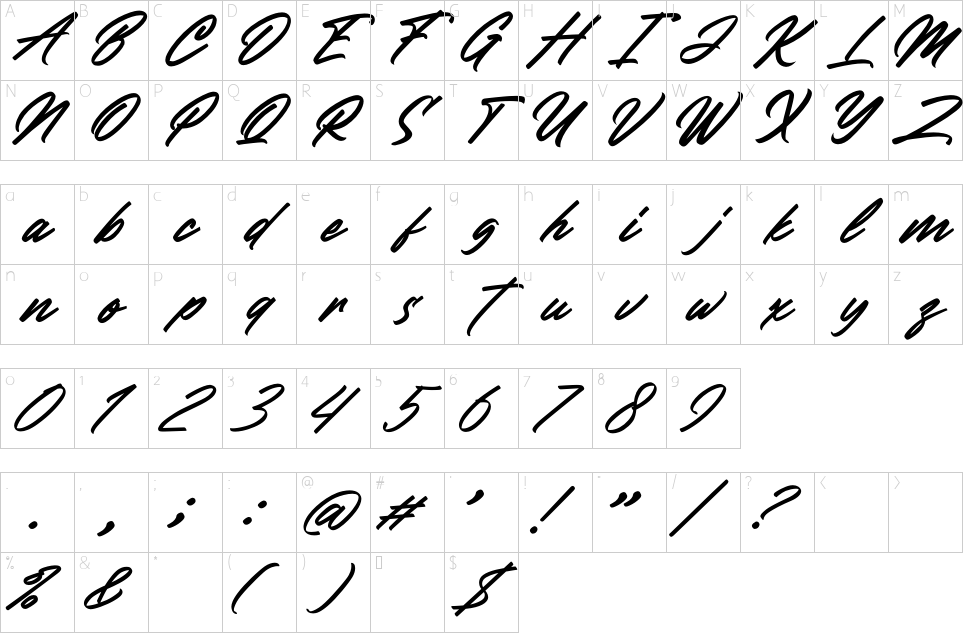
A fonte ‘Delegante Champion’ foi projetada por Yadi Setiawan e é uma deliciosa escolha para qualquer projeto onde você busca uma personalidade única. Inspirada em linhas curvadas e delicadas, essa fonte é perfeita para criar um estilo elegante e sofisticado. Ideal para gráficos digitais, logos e materiais de branding, a ‘Delegante Champion’ adiciona um toque de criatividade e elegância a qualquer projeto. Download esta fonte e veja como ela complementa seu trabalho, disponível tanto para sistemas operacionais Windows quanto para Mac. Com apenas 914 downloads, você está entre poucos que já experimentaram essa beauté de fontes. Não perca essa oportunidade para enriquecer seu trabalho com uma fonte única e moderna.